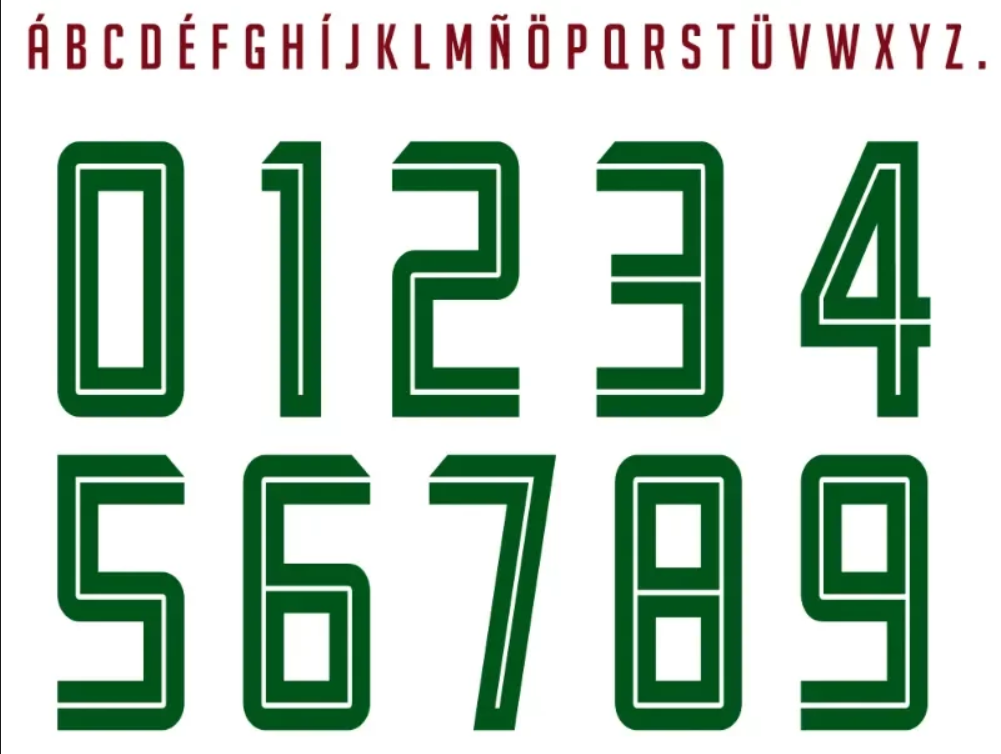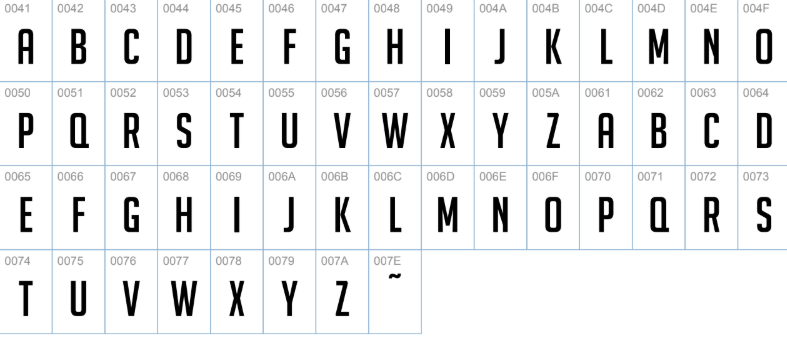
A parceria entre o Fluminense e a Under Armour, que vestiu o Tricolor Carioca nas temporadas 2017 e 2018, ficou marcada por uniformes com designs distintos e tecnologia de performance. Além das tradicionais listras em grená, verde e branco, um elemento chave da identidade visual daqueles kits era a tipografia exclusiva usada para os nomes e números dos jogadores.
Se você é designer, entusiasta de camisas de futebol ou um torcedor do Flu querendo criar artes personalizadas, ter esta fonte é essencial. Ela captura perfeitamente o visual usado por ídolos daquele período e permite recriar mockups e projetos com fidelidade total.
- Nome da Fonte: Fluminense 2017-2018 (Estilo Under Armour)
- Uso Recomendado: Ideal para mockups de uniformes, personalização de camisas (vetorização para silk ou transfer), criação de artes para redes sociais, flyers e qualquer projeto gráfico temático do Fluminense.
Diferente das fontes mais arredondadas ou clássicas, a tipografia da Under Armour para o Fluminense em 2017-18 é robusta, moderna e geométrica. Ela possui cantos vivos e um design “blocado”, que transmite força e excelente legibilidade em campo.
Com uma leve inclinação (itálico sutil) em sua versão padrão, ela passa uma sensação de movimento e velocidade. Foi um design marcante que se diferenciou bastante das fontes usadas por concorrentes como Nike ou Adidas na mesma época, dando uma assinatura visual única para o Tricolor nas disputas do Campeonato Brasileiro e da Copa Sul-Americana.